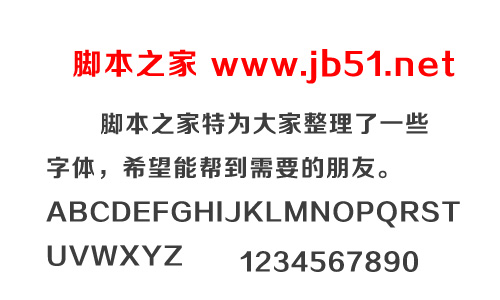
方正正粗黑簡體字體是方正字體庫中的一種中文字體,方正正黑的設(shè)計源于“北大方正集團(tuán)”的標(biāo)志字體,是一套為企業(yè)VI系統(tǒng)設(shè)計的專用字體。這款字體的字面開闊,重心較高,筆畫有對稱的鏡像感,右下角折筆處均呈圓弧形,撇捺筆畫的起筆與收筆由粗漸細(xì),簡潔時尚。方正正黑的筆形結(jié)合了黑體特征,拓展成為一款家族化的黑體字。方正正黑家族包含6款字重,已被廣泛應(yīng)用于各類報紙、雜志、廣告、企業(yè)形象、包裝和電視廣播媒介中。喜歡的朋友們可以前來下載使用。